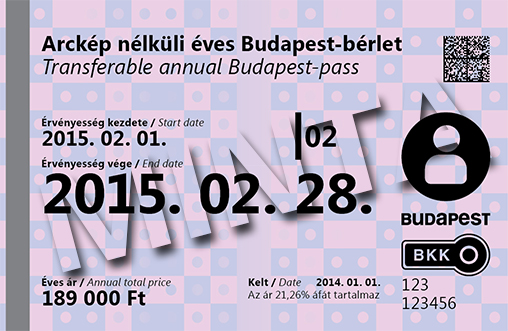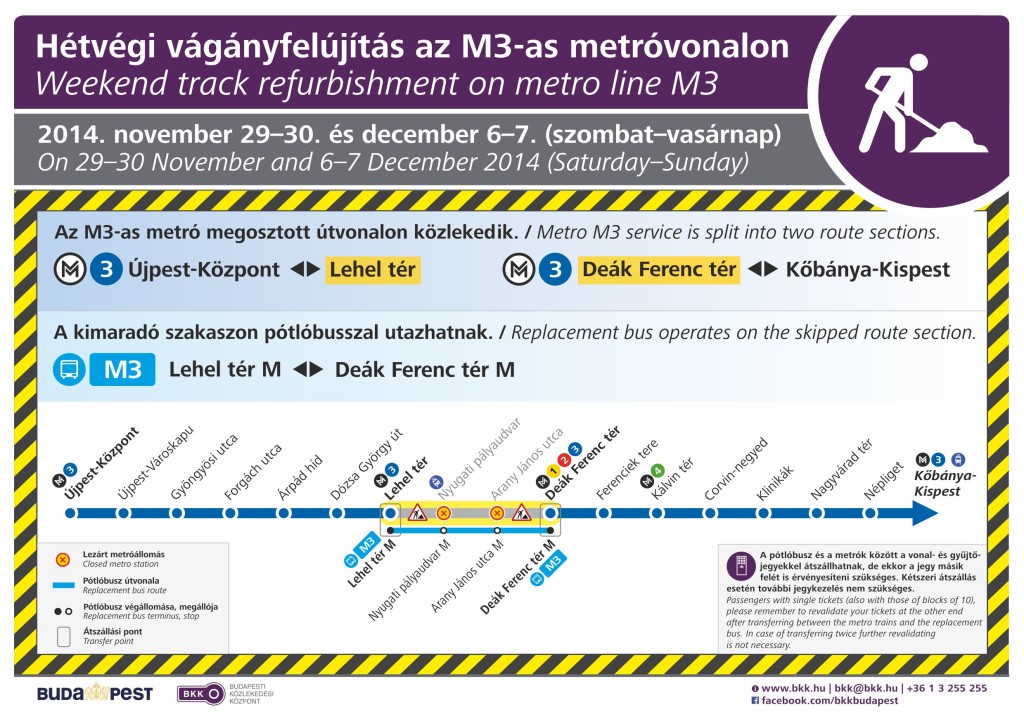
Rechtsbündiger Rausatz
ich erstelle zur Zeit eine große Ausstellungstafel (Größe 2,40 m x 3,20 m). Für die Schriftgröße habe ich 55 pt gewählt.
Da der Text zweisprachig (deutsch und englisch) verwendet werden muss, habe ich für die einzelnen Textblöcke rechtsbündigen und linksbündigen Rausatz verwendet. Also der endlische Text ist rechtsbündig und der deutsche Text linksbündig. Insgesamt gibt es drei Blöcke.
Die grafische Wirkung bei Verwendung von rechtsbündigen Rausatz in Verbindung mit einer linksbündigen Spalte wird betont.
Jetzt kommt das "aber": Ich weiß, dass die Lesegeschwindigkeit herabgesetzt ist. Was mich nicht sonderlich stören würde. Die Zeilen sind nicht zu lang und die einzelnen Sätze sind kurz und verständlich gehalten. Leider gibt es auch Aufzählungen im Text. Und das sieht beim rechtsbündigen Rausatz nicht schön aus. Ich habe hier keine Idee wie ich das lösen könnte....
Rausatz – wirklich? Wie umfangreich ist das denn?
Vielleicht hilft ja auch schon einen einigermaßen ausgewogenen Flattersatz daraus zu machen, dass die Aufzählungen besser aussehen ... :-?
Vielleicht bei den linksbündigen Aufzählungen einen linken Einzug und bei den rechtsbündigen einen rechten Einzug anlegen, damit die Aufzählungen nicht wegen ihrer Länge (bzw. Kürze) zu sehr rausfallen.
Zeig uns doch mal ein paar Beispiele und was dich genau stört. Dann könnte man konkreter helfen :nicken:
Blocksatz ist eine Möglichkeit. Wobei bei so großen Ausstellungstafeln der Zeilenumbruch durch semantische Optimierung festgelegt wird, daher Rausatz/Flattersatz und keine Worttrennungen. Was sich beim Blocksatz schwierig darstellt. Ich werde den Blocksatz dennoch in Erwägung ziehen, da ein rechtsbündiger Flattersatz/Rausatz genauso schwierig zu lesen ist.
Also ich würde den englischen Text nicht lesen wollen … wäre es denn so schlimm, alles linksbündig zu setzen? Die Linie würde ich evtl. auch weg lassen und dafür die beiden Sprachen durch verschiedene Farben oder Schriftschnitte voneinander abzusetzen.
Wenn eine Trennlinie verwendet wird, wäre Linksbündigkeit in beiden Spalten mein Favorit in Verbindung mit Flattersatz.
Zumal die Bündigkeit ohnehin kein hinreichendes Merkmal ist, um den Leser schnell erfassen zu lassen, wo der Text in seiner präferierten Sprache steht. Das ist aber wichtig, weil Leser sonst abgeschreckt werden und anscheinend schnell ganz aufgeben, wenn sie bei jedem 2. Absatz erst ihnen ggf. unverständliche Wörter auseinanderpflücken zu müssen, bevor sie ihre Sprache finden.
Gestalter mehrsprachiger Leitsysteme oder Museumsbeschilderungen wissen das anscheinend auch – und heben die zweite Sprache meist besonders hervor, z.B. durch Schriftschnitte (Englisch kursiv), Farbe (Englisch grau) etc. etc. So etwas würde ich hier auch erwägen.
Wir haben das mit mehrsprachigen Websites auch festgestellt. Textbasierte Hinweise (z.B. EN, DE am Absatzanfang) reichen nicht. Visuelle clues (wie eben Farbe oder signifikant unterschiedliche Schriftschnitte) funktionieren viel besser.
Ich werde beide Sprachen linksbündig setzen und die eine Sprache mittels Farbe hervorheben. Aufgrund der Textmenge verwende ich keinen kursiven Schriftschnitt, da dieser nicht so gut lesbar ist wie eine serifenlose Schrift.
Für mich ist ein kursiver Schriftschnitt eine Form der Auszeichnung, bei dem die Grauwirkung des Textes nicht verändert wird. Einen Fließtext komplett in kursiv zu setzen – naja...
Sagt man nicht, dass der "normale" Schriftschnitt einer Typo am besten lesbar ist und man den Fließtext nicht komplett kursiv setzen sollte? Somit bleibt ja nur bei einem zweisprachigen Produkt die Unterscheidung mittels Farbe. Ich lasse mich aber gerne auch aufklären.
Ich glaube solche Verallgemeinerungen treffen immer weniger zu, bei der Fülle an Schriften, die es heute gibt. Ich habe mal Inkunabeln gesehen, die komplett in Kursiv gedruckt waren und die Auszeichnungen waren da aufrecht. Schlecht lesbar war das nicht. Ich würde aber auch eher zwei Farben nehmen, da Kursiv ja vom Gefühl her, doch eher als Ersatz-, Auszeichnungs- oder Zweitschnitt angesehen wird und die Aufrechte als quasi Hauptschnitt™. Das fände ich im Zweifelsfall zu Herarchisierend.
Wenn ich eine Ausstellung in Brüssel mit flämischem und französischem Text gestalten sollte, wäre ich in dieser Frage sicher auch ganz vorsichtig. Aber Deutsch und Englisch werden doch praktisch nie völlig symmetrisch eingesetzt. Da ist immer eine die Lokalsprache und die andere die für Anderen.